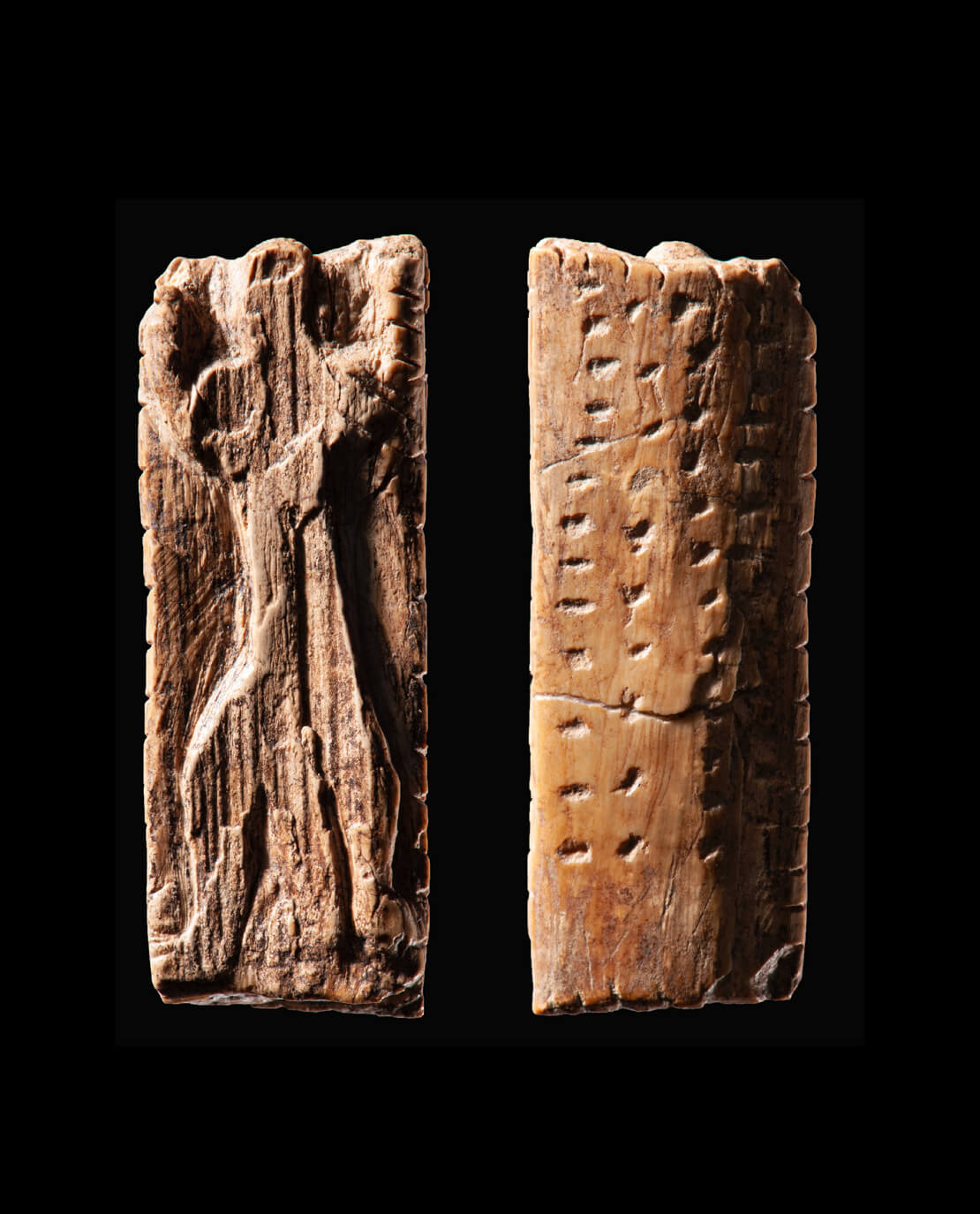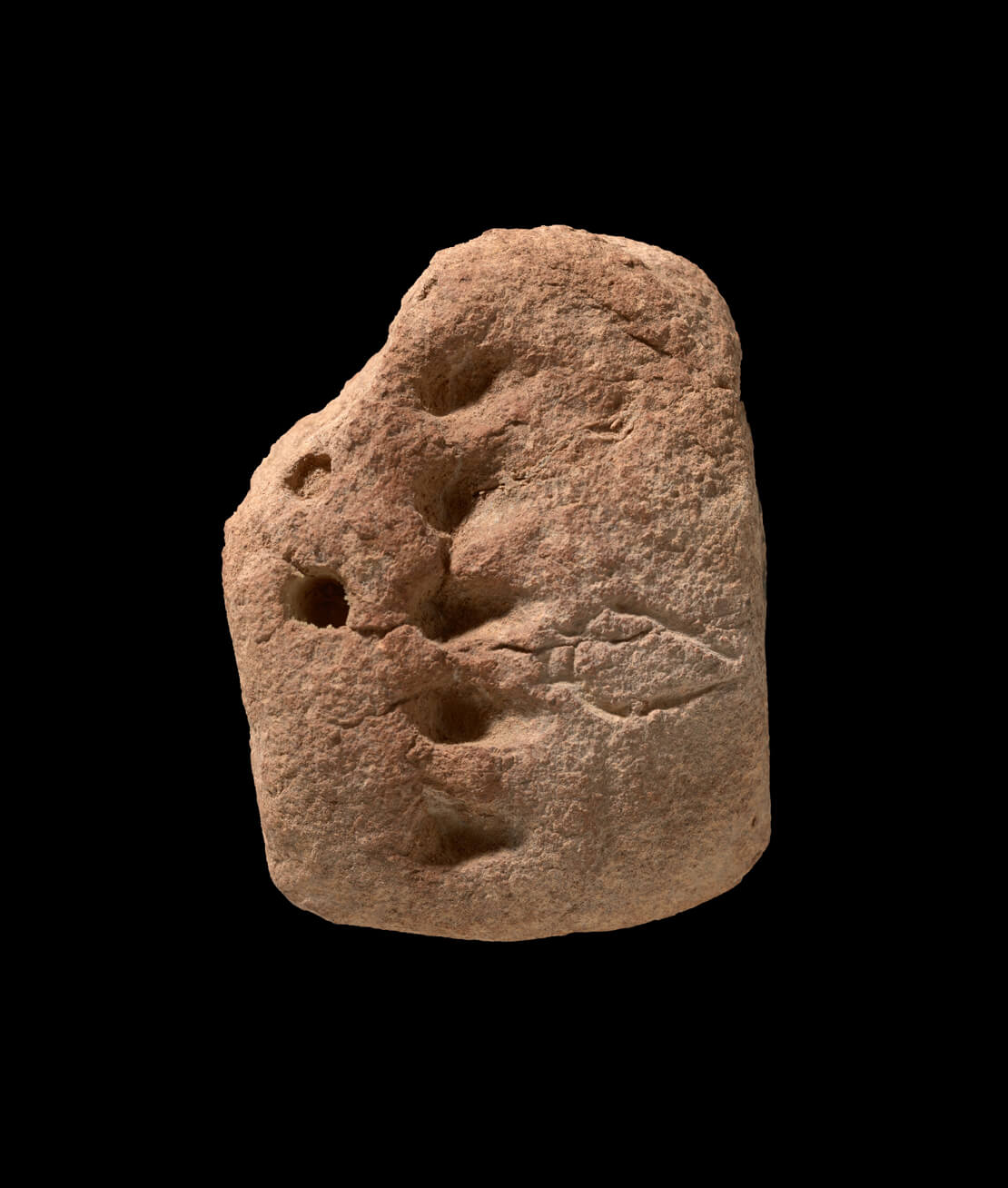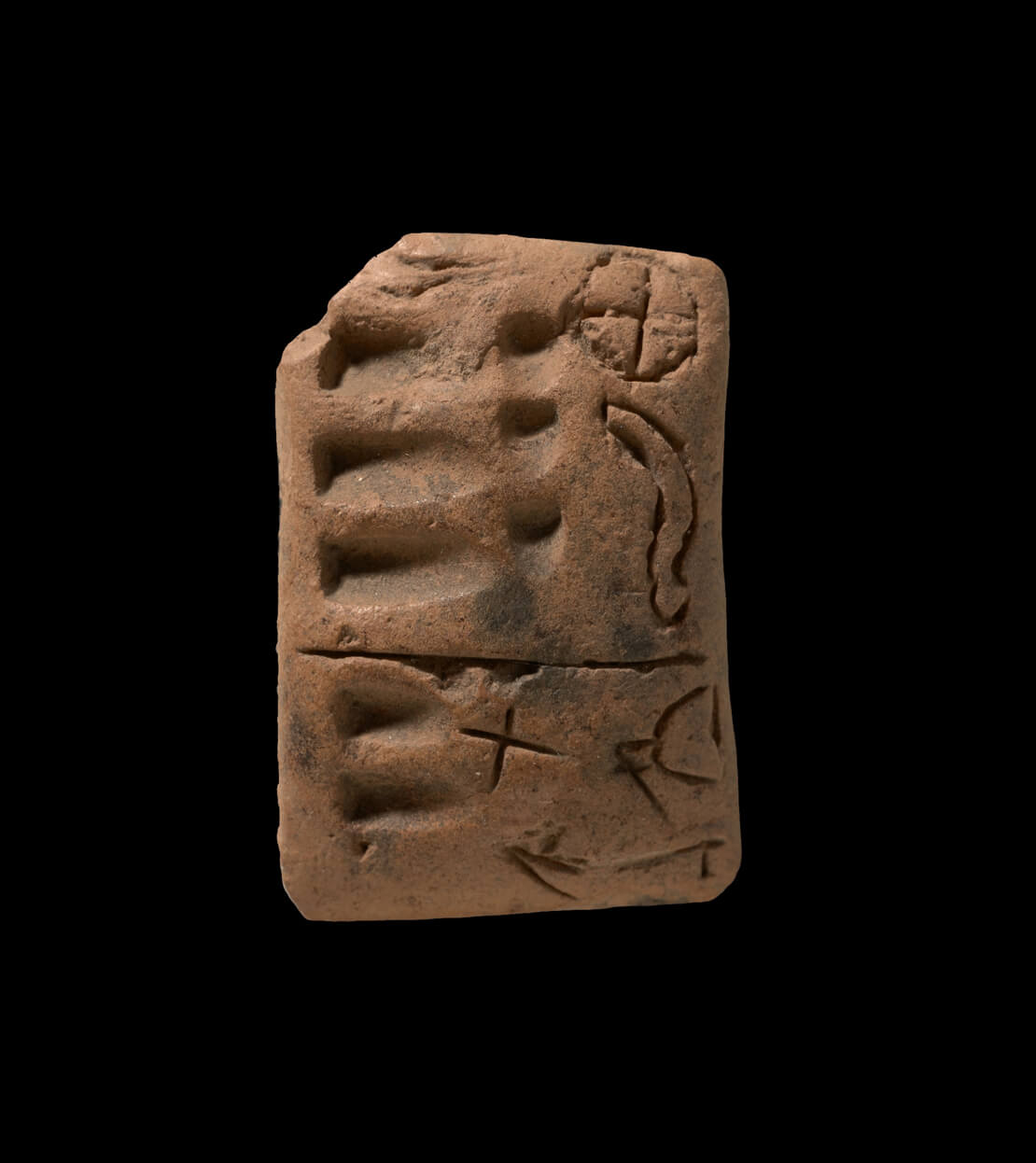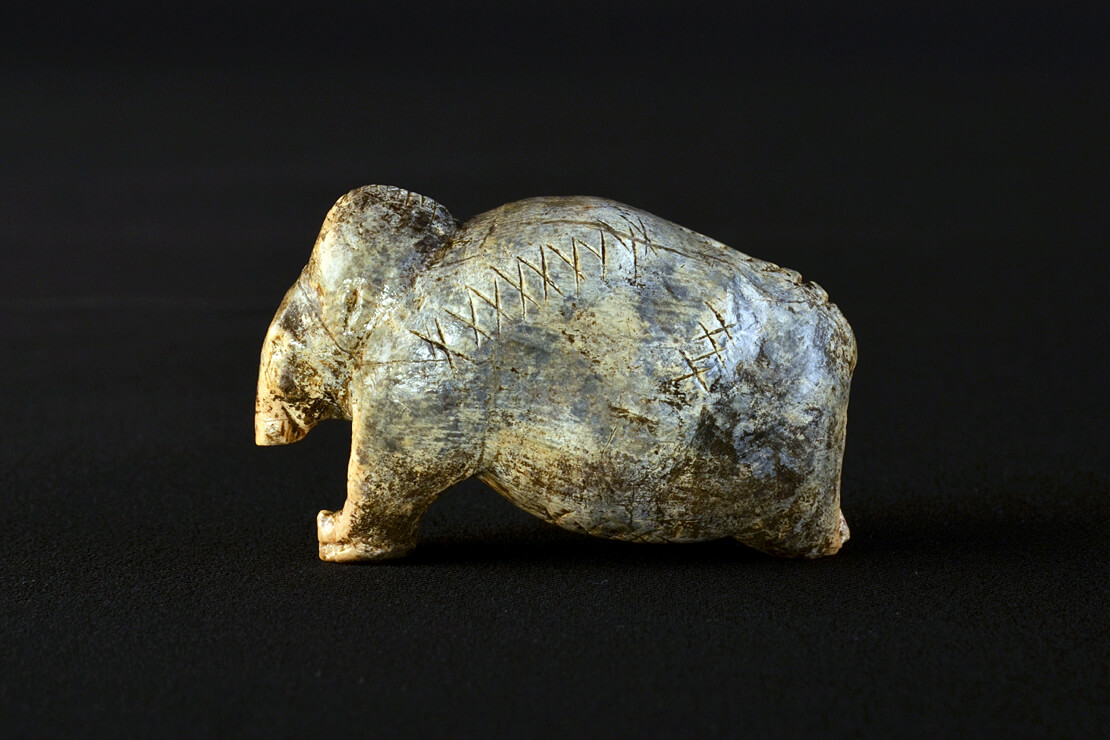
Vorläufer der Schrift: Zeichen auf Steinzeit-Funden analysiert
Forscher haben herausgefunden, dass 40.000 Jahre alte Ritzungen auf Steinzeit-Artefakten eine ähnliche Informationsdichte aufweisen wie frühe Keilschriften. Eine computergestützte Analyse zeigt, wie früh der Mensch visuelle Zeichen zur Wissensspeicherung nutzte.
Vorläufer der Schrift
Die Mammut-Figurine aus der Vogelherd-Höhle ist etwa 40.000 Jahre alt und trägt auf ihrer Oberfläche mehrere Reihen von Kreuzen und Punkten. © Universität Tübingen / Hildegard Jensen
Linien, Punkte, Kerben und Kreuze, die sich in regelmäßigen Abständen wiederholen: Auf bis zu 45.000 Jahre alten Fundstücken aus der Altsteinzeit finden sich gezielt angebrachte Zeichenfolgen. Zu den untersuchten Artefakten gehören unter anderem kleine Skulpturen aus Mammutstoßzähnen, die in Höhlen der Schwäbischen Alb entdeckt wurden. Laut der Archäologin Ewa Dutkiewicz vom Museum für Vor- und Frühgeschichte der Staatlichen Museen zu Berlin stammen die Artefakte aus einer Zeit, kurz nachdem der Homo sapiens begann, von Afrika aus Europa zu besiedeln – zehntausende Jahre vor den Anfängen der uns heute bekannten Schrift.
Statistischer Fingerabdruck der Steinzeit
Gemeinsam mit dem Sprachforscher Professor Christian Bentz (Universität des Saarlandes) analysierte Ewa Dutkiewicz über 3.000 geometrische Zeichen auf rund 260 historischen Objekten. Mithilfe von Computermethoden aus der quantitativen Linguistik ermittelte das Team messbare Eigenschaften wie Struktur und Häufigkeitsmuster. »Wir kommen mit unserer Forschung dem statistischen Fingerabdruck der Zeichensysteme auf die Spur«, erklärt Christian Bentz. »Die steinzeitlichen Zeichensequenzen sind eine frühe Alternative zur Schrift.«
Dabei ging es primär nicht um eine inhaltliche Entschlüsselung, sondern um messbare Eigenschaften wie Struktur, Häufigkeitsmuster und die Vorhersagbarkeit von Zeichenabfolgen.
Adorant
Der sogenannte „Adorant“ aus der Geißenklösterle Höhle ist ca. 40.000 Jahre alt. Es handelt sich um eine kleine Elfenbeinplatte mit einer anthropomorphen Figur und mehreren Reihen von Kerben und Punkten. Die Anordnung dieser Markierungen lässt auf ein Notationssystem schließen, insbesondere die Reihen von Punkten auf der Rückseite der Platte. © Landesmuseum Württemberg / Hendrik Zwietasch
Komplexität auf dem Niveau der Proto-Keilschrift
Die Auswertungen belegen, dass die repetitiven Sequenzen zwar keine gesprochene Sprache abbilden, aber einem klaren System folgen. Infolge ihrer hohen Wiederholungsraten weisen sie eine Komplexität und Informationsdichte auf, die mit den frühesten Proto-Keilschrifttafeln aus Mesopotamien vergleichbar ist.
Keilschrifttafel
Die Proto-Keilschrifttafel aus der Uruk V Periode (VAT 15085), etwa 3500 bis 3350 Jahre alt, trägt auf der linken Seite Zahlzeichen und auf der rechten Seite ein Ideogramm, das ein Gefäß mit unbekanntem Inhalt darstellt. © Staatliche Museen zu Berlin, Vorderasiatisches Museum / Olaf M. Tesmer
Dieses Ergebnis überraschte das Forschungsduo. Ewa Dutkiewicz erläutert: »Je mehr wir uns allerdings damit beschäftigt haben, umso deutlicher wurde, wie strukturell ähnlich die frühe Proto-Keilschrift den viel älteren paläolithischen Zeichensequenzen ist.« Dabei stellte sie fest, dass die Informationsdichte auf kleinen Figurinen höher ausfällt als auf Werkzeugen.
Zeichen als Werkzeug der Koordination
Was genau die Steinzeitmenschen mit diesen abstrakten Zeichenfolgen festhalten wollten, bleibt vorerst verborgen. Die neuen Erkenntnisse könnten jedoch dabei helfen, »mögliche Interpretationen einzugrenzen«, so Dutkiewicz. Sie verweist darauf, dass die Gegenstände so gefertigt waren, dass sie gut in der Hand lagen und von den damaligen Menschen bei sich getragen wurden – vermutlich, um Wissen festzuhalten und Gruppen zu koordinieren. Christian Bentz resümiert die Entwicklung: »Die Fähigkeit des Menschen, Informationen über Zeichen und Symbole zu kodieren, hat sich über viele Jahrtausende entwickelt. Die Schrift ist nur eine spezifische Ausformung aus einer langen Reihe an Zeichensystemen.«
Proto-Keilschrift Uruk
Die Proto-Keilschrifttafel aus der Uruk IV Periode (VAT 14774), etwa 3350–3200 Jahre alt, zeigt auf der linken Seite Zahlzeichen und auf der rechten Seite vielfältigere Ideogramme. Zusätzlich ist die Tafel durch eine horizontale Linie unterteilt. © Staatliche Museen zu Berlin, Vorderasiatisches Museum / Olaf M. Tesmer
Die Untersuchung ist Teil des vom Europäischen Forschungsrat geförderten Projekts EVINE (Evolution Visueller Informationskodierung). Die detaillierten Ergebnisse wurden online in den Proceedings of the National Academy of Sciences (PNAS) publiziert.